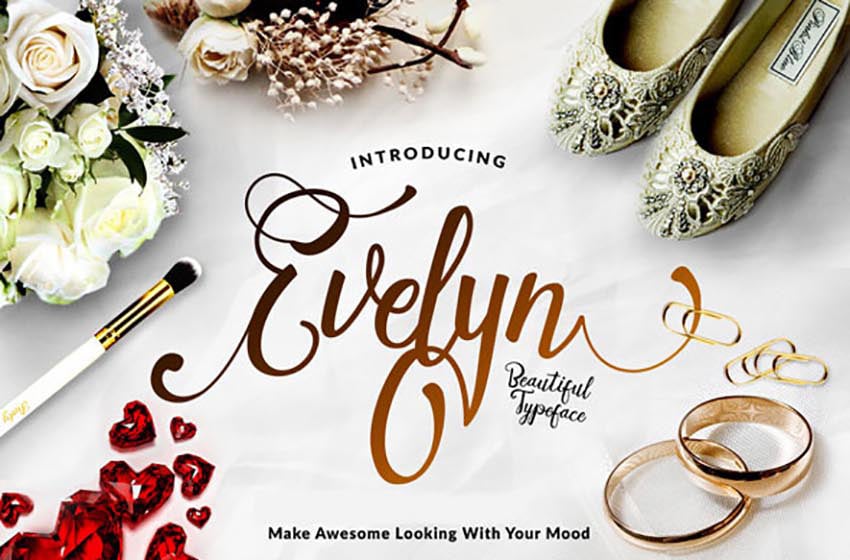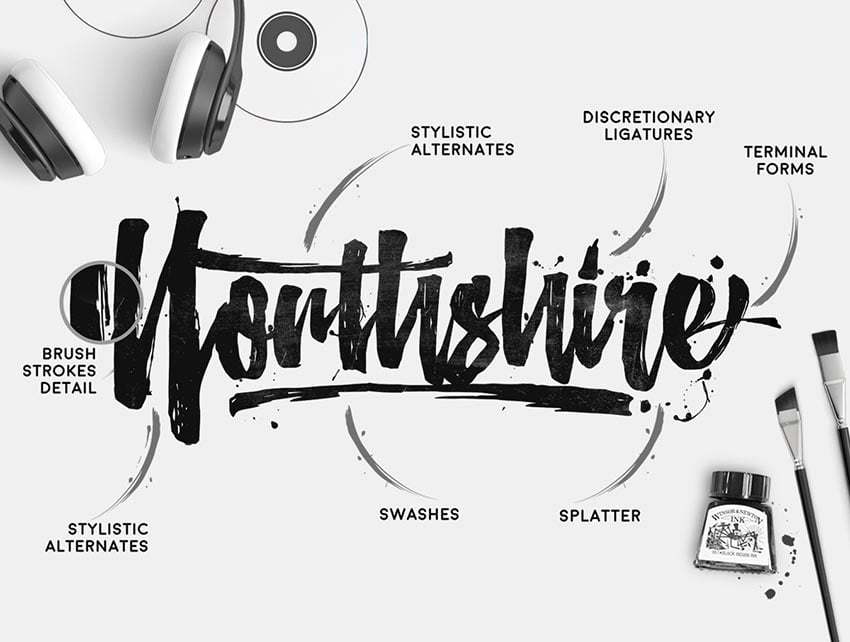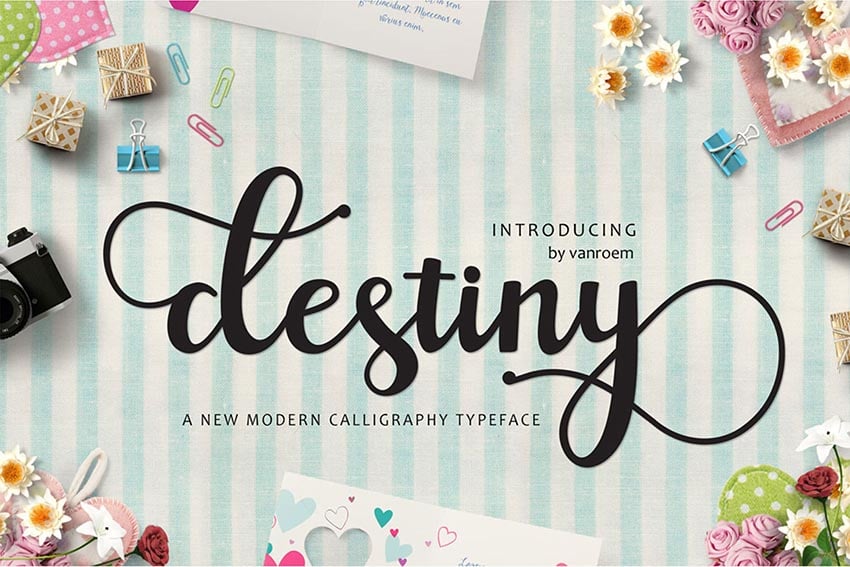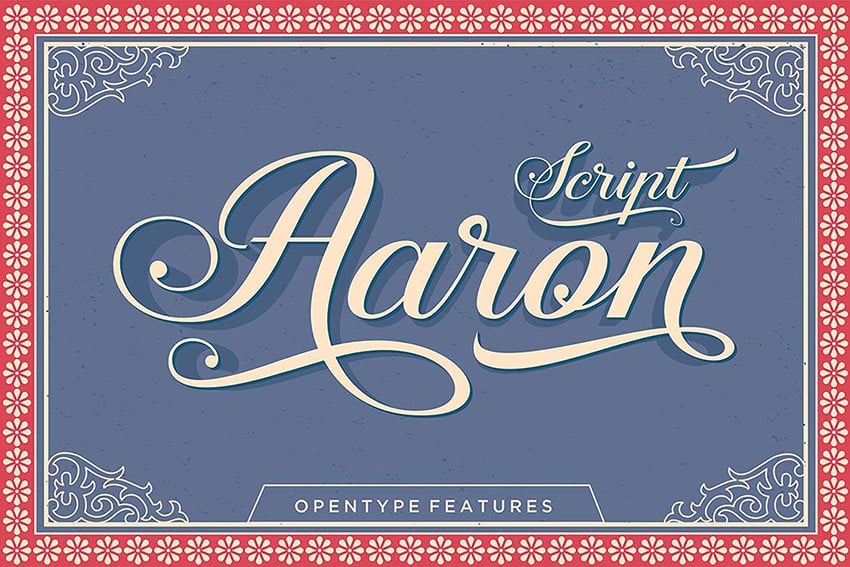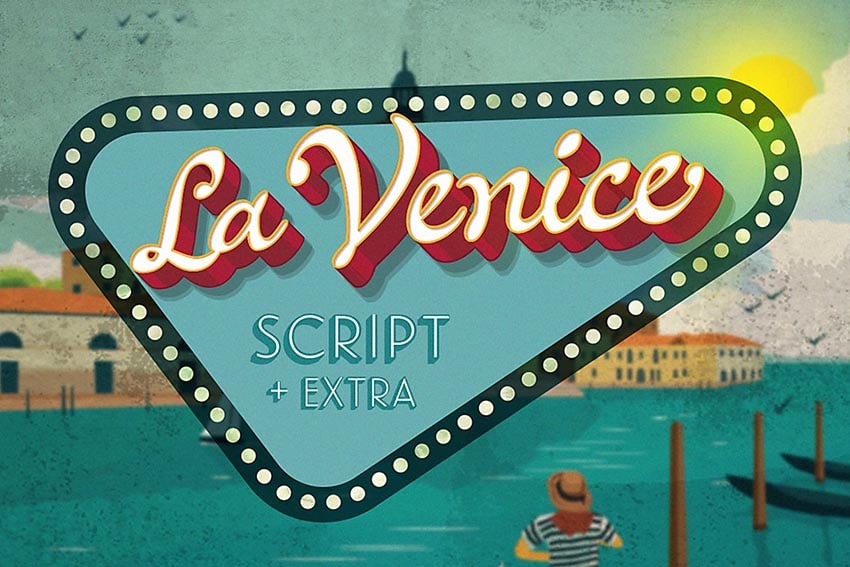
Рукописные шрифты (Cursive).
Эти шрифты представляют собой попытку имитации
человеческого почерка.
Напр. : Zapf Chancery, Author, Comic Sans.
Курсив прописной.
Рукописный шрифт или скрипт – это имитация почерка от руки. Такие шрифты обычно не годятся для набора основного текста, зато их активно можно использовать для оформления заголовков, цитат или подписей на слайдах. Скрипты, как и почерки, очень разнообразны – каждый передает свое настроение. Мы сделали для вас подборку качественных рукописных шрифтов, которые подойдут на любой случай.
Простой рукописный шрифт с прописными буквами, который легко читается и отлично будет смотреться в заголовках. Доступен в двух начертаниях – Regular и Bold.
25 лучших стильных рукописных шрифтов
Знание своего направления среди различных стилей шрифтов – ключ к отличному дизайну. Один из самых быстрых способов повысить уровень дизайна ваших работ – это использование стильного курсивного шрифта. Просмотрите подборку 25 невероятных рукописных шрифтов, которые вы наверняка захотите использовать в вашем следующем творческом проекте!
25 стильных рукописных шрифтов
Если вы любите шрифты, написанные от руки, винтажный почерк или волнистое начертание текста, у нас есть уникальные прописные стили именно для вас!
Bromello Typeface
Давайте начнём с этого очаровательного, извилистого шрифта. Этот красивый, современный курсив выделяется прекрасным, созданным в ручную дизайном, который, несомненно, выделит любой постер среди всех остальных. В этот пакет входит полный набор символов, цифр, а также удобные стилистические альтернативы.
Marchy Script Font
Погрузитесь в рукописную атмосферу с этим веселым шрифтом. Современное начертание шрифта выделяется каллиграфическим стилем, выполненным вручную, с декоративными символами и «танцующими» базовыми линиями. Также включены более 430 альтернативных символов, а также все необходимые стандартные буквы.
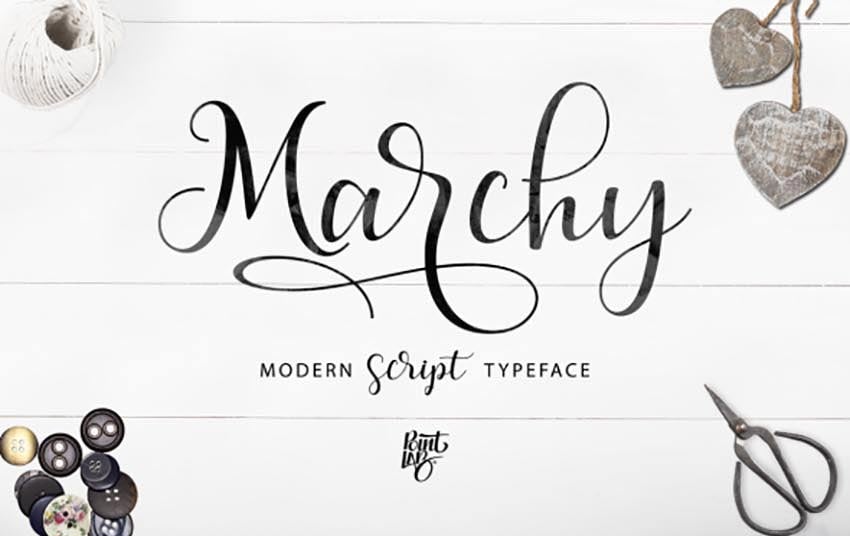
Brushgyo Typeface
Идеально подходит для дизайна логотипа, или любого другого дизайна, обслуживающего типографию; этот сногсшибательный шрифт отличается наличием заглавных и прописных букв, цифр и всех знаков пунктуации, которые вам необходимы. Загрузите его уже сегодня, чтобы наслаждаться всем, что предлагает вам этот уникальный шрифт!
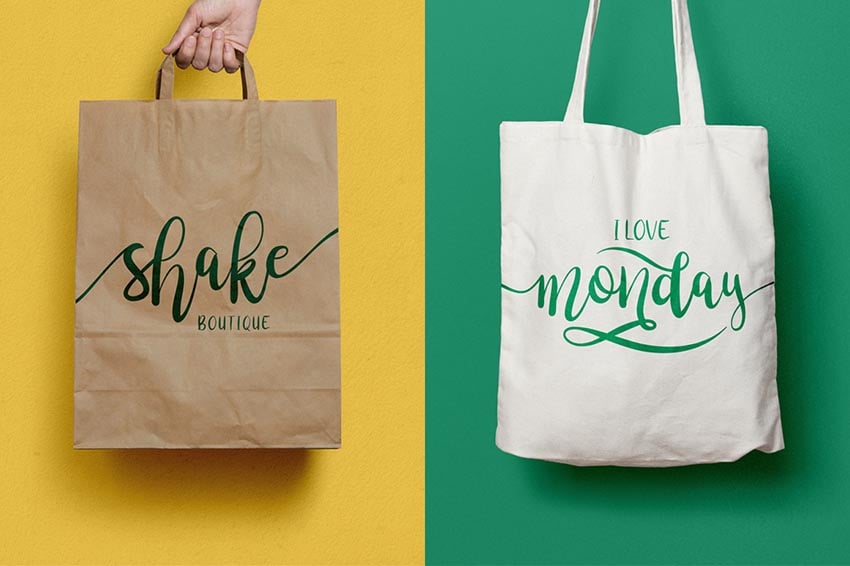
Beautiful Friends Font
Мы думаем, все наши друзья на Envato Tuts+ — прекрасны! И с помощью этого шрифта с завитками вы создадите красивые и впечатляющие работы, полные веселья и энергии. Создавайте всё, что угодно, превращая его в само очарование, с помощью уникального стиля, наполненного милыми завитками и более тысячи дополнительных символов.
Leviafan Script Font
Рукописные шрифты – это всегда верное направление, если вы хотите создать креативные дизайн-работы, оказывающие сильное впечатление на публику. Этот прекрасный курсивный шрифт действительно лучший из лучших! Наслаждайтесь невероятным дизайном ручной работы, вдохновленным винтажными надписями от руки. Используйте этот шрифт в ваших следующих креативных проектах для достижения невероятных результатов!
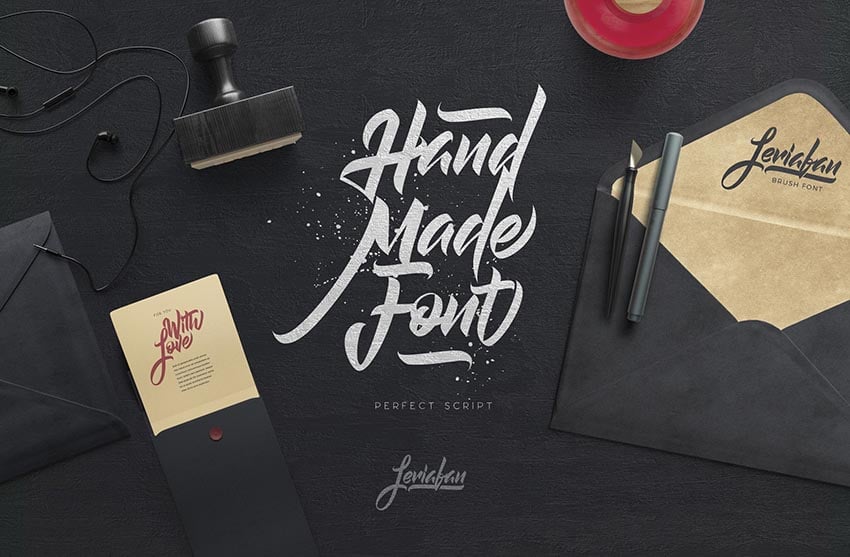
Risthi Script Font
Продемонстрируйте ваш потрясающий взгляд на вещи с помощью этого современного каллиграфического стиля шрифта. Вдохновленный стильными курсивными шрифтами, этот рукописный шрифт идеально подойдет для любого современного дизайна. В загрузочный файл включены семь файлов шрифтов и даже версия шрифта для веб.
Qoobly Typeface
Получите подлинное ощущение ручной работы с этим невероятным рукописным шрифтом. Он оформлен толстыми закрученными линиями с акцентами на более тонких, изящных, и мы уверены, что вы обязательно найдете применение этим прекрасным стилям шрифтов. В данный пакет входят два разных шрифта, которые вы сможете легко использовать на Macs, или PCs.
Afrile Script Font
Благородный шрифт с роскошными плавными кривыми; шрифт Afrile – безусловно прекрасный! Особенность этого элегантного стиля шрифта – мягкий каллиграфический дизайн, в который входят все буквы, цифры и пунктуация, которая вам только не понадобиться для выдающихся логотипов и печатной продукции!